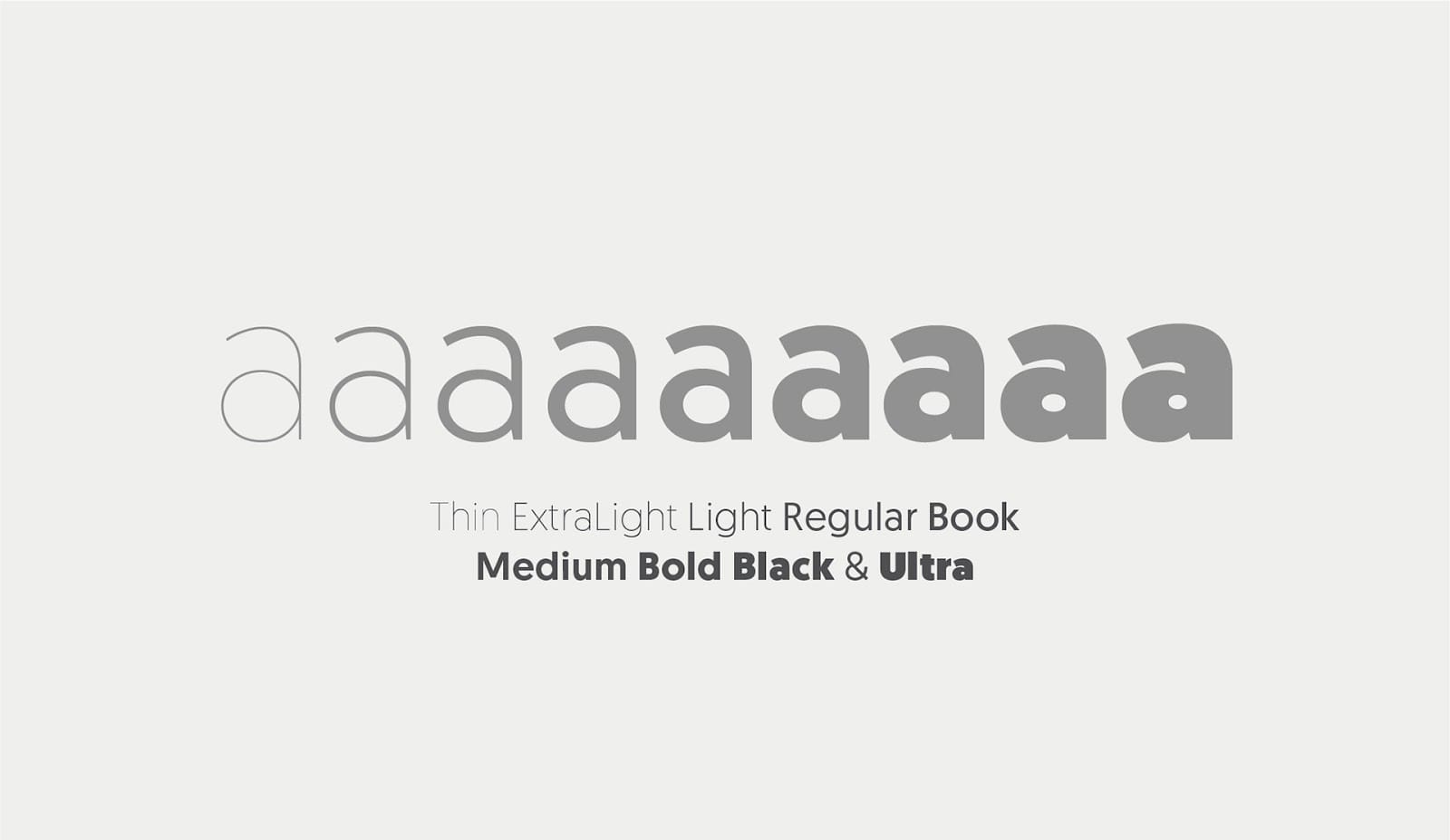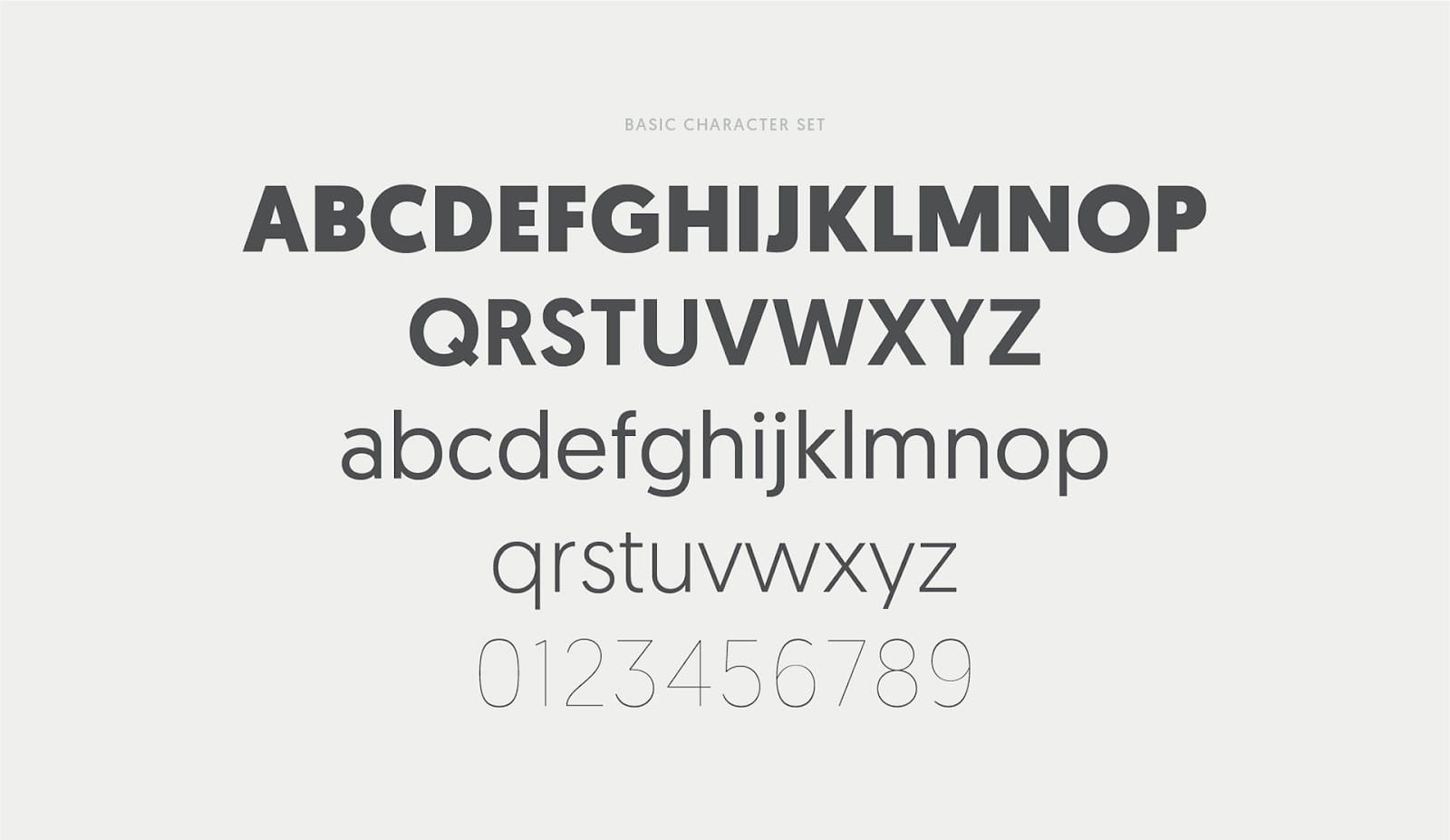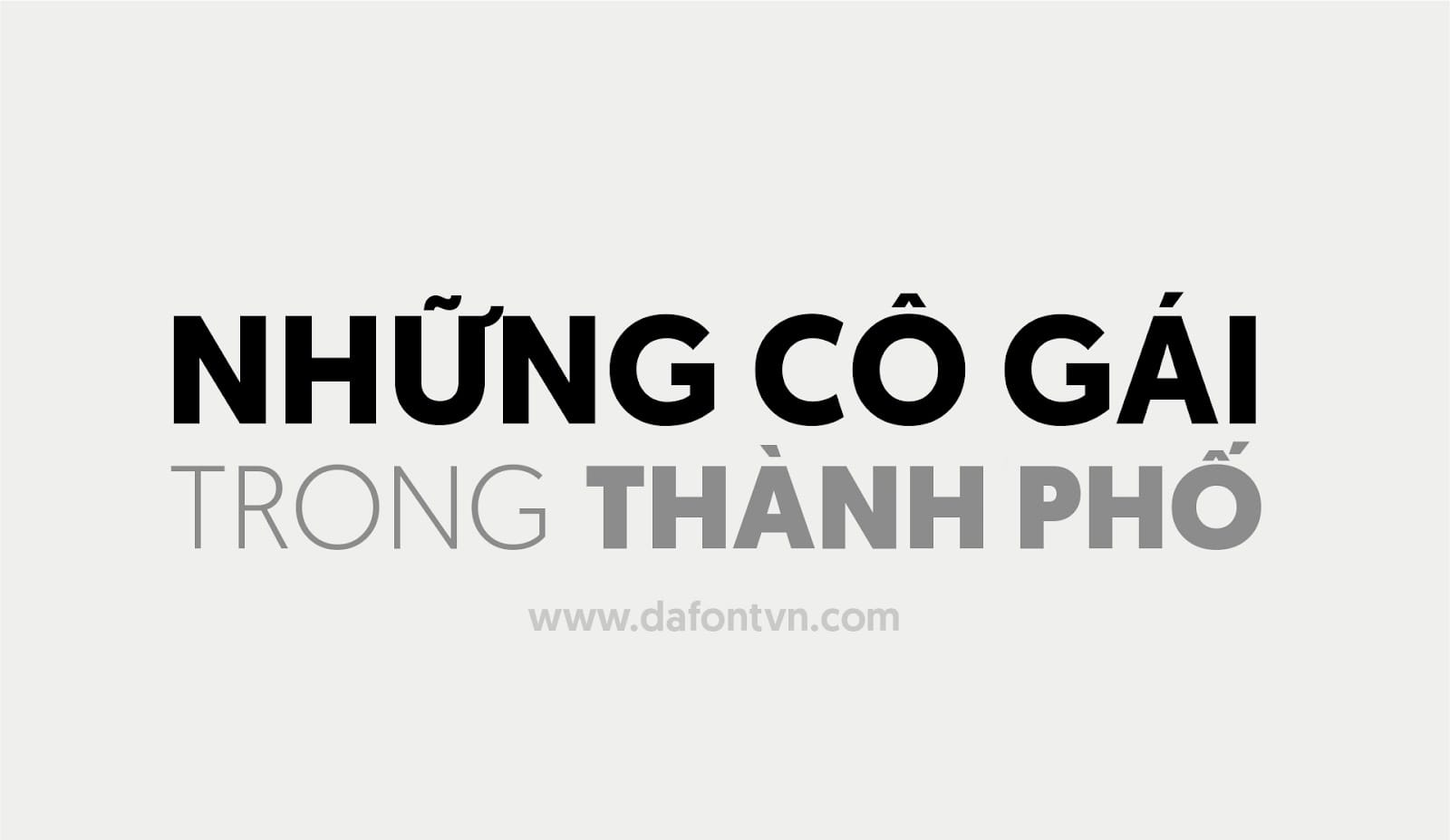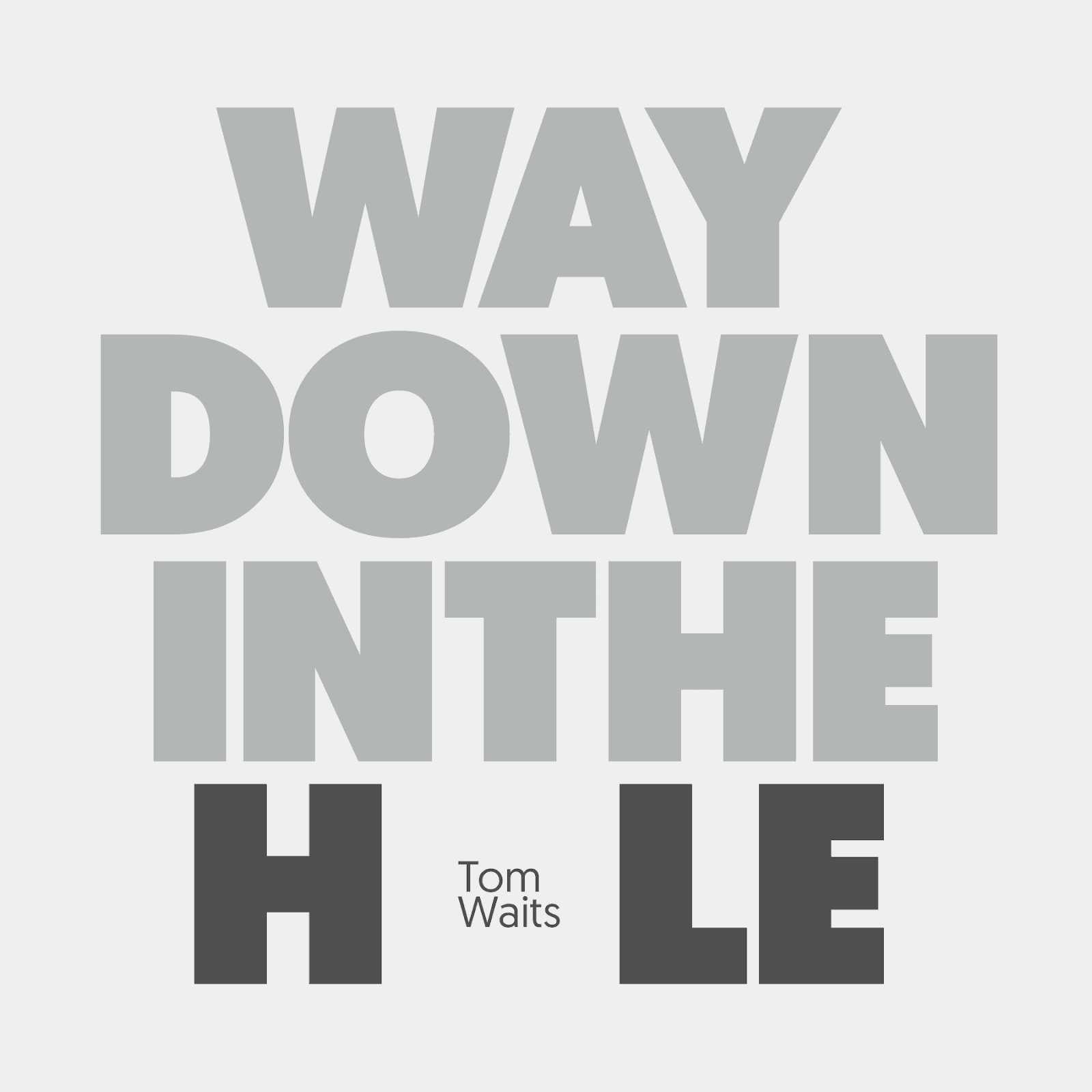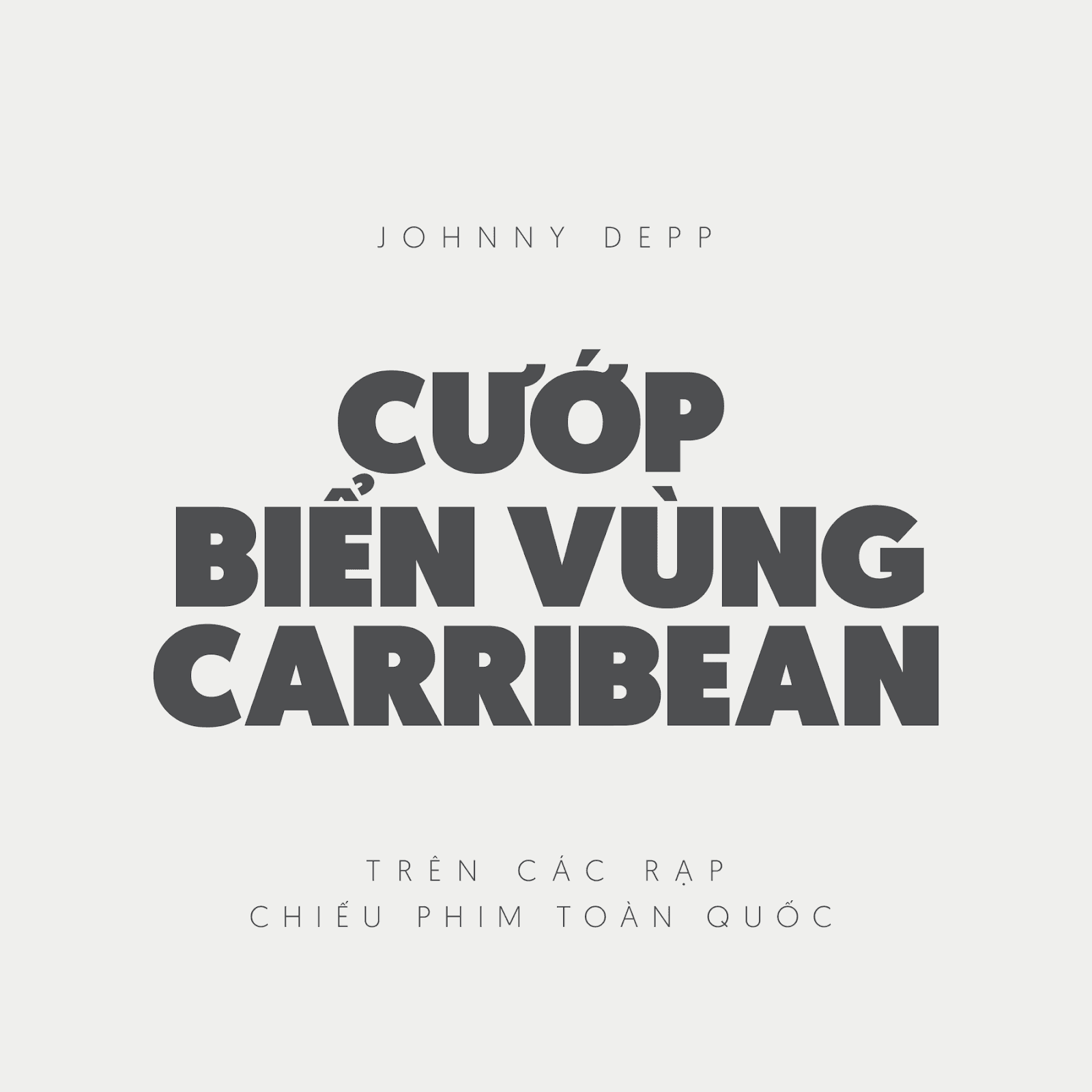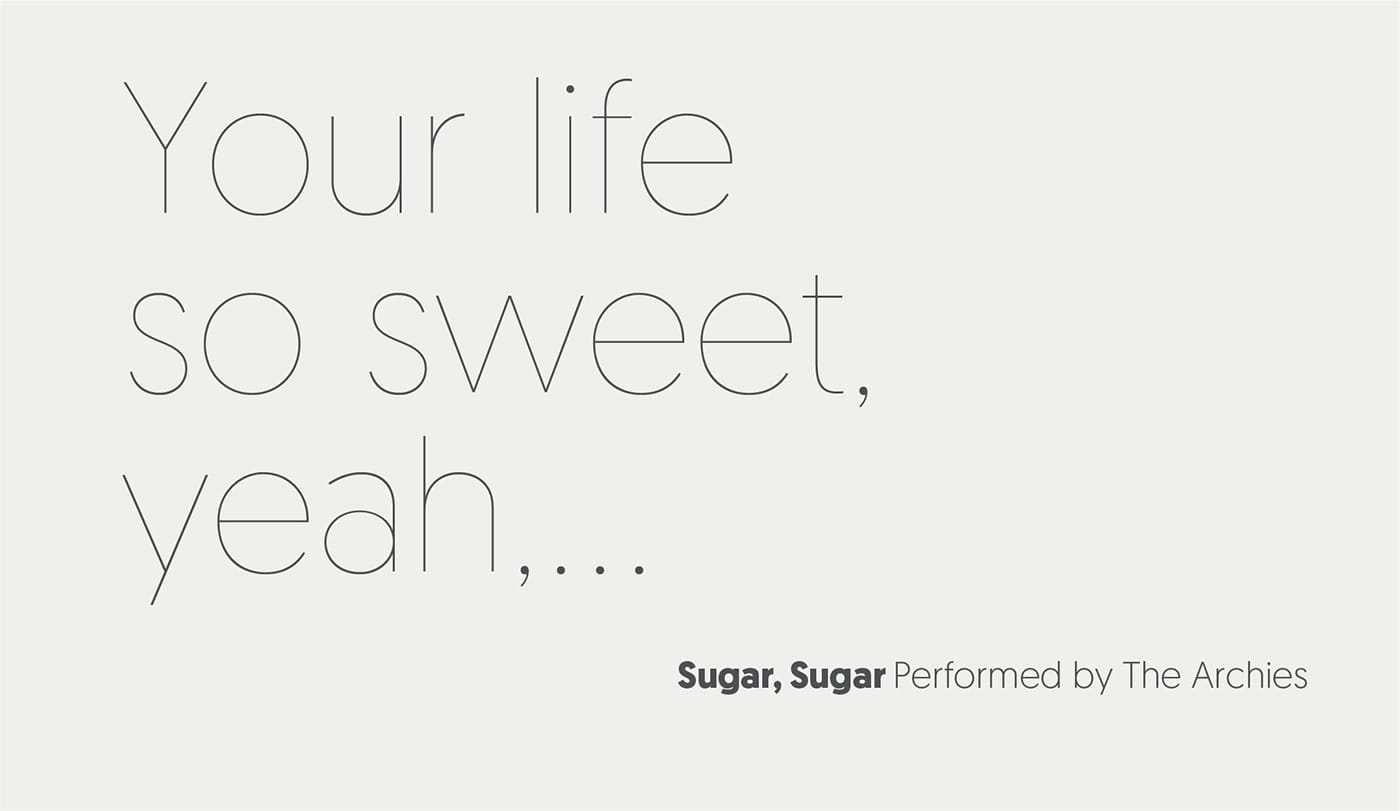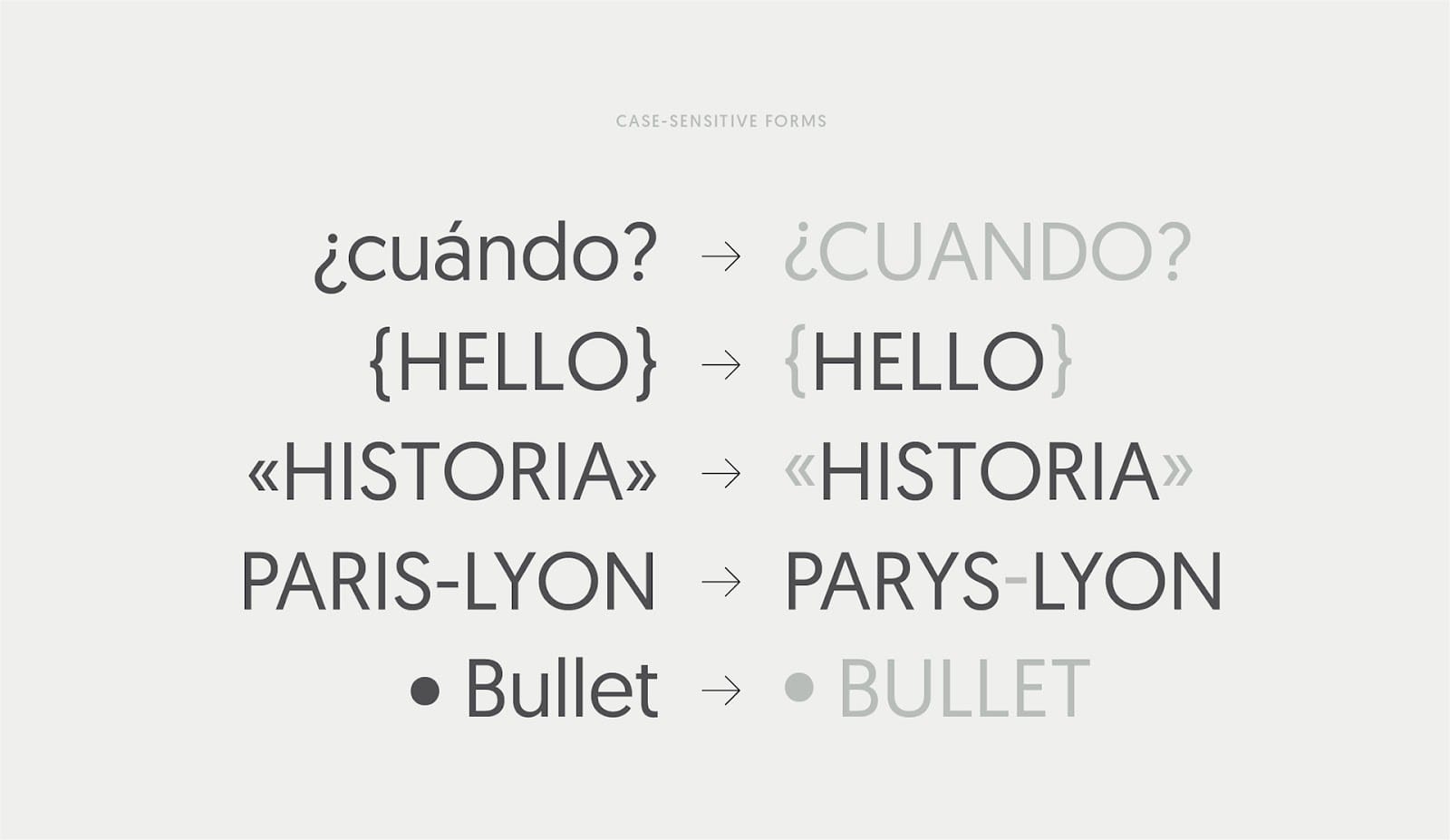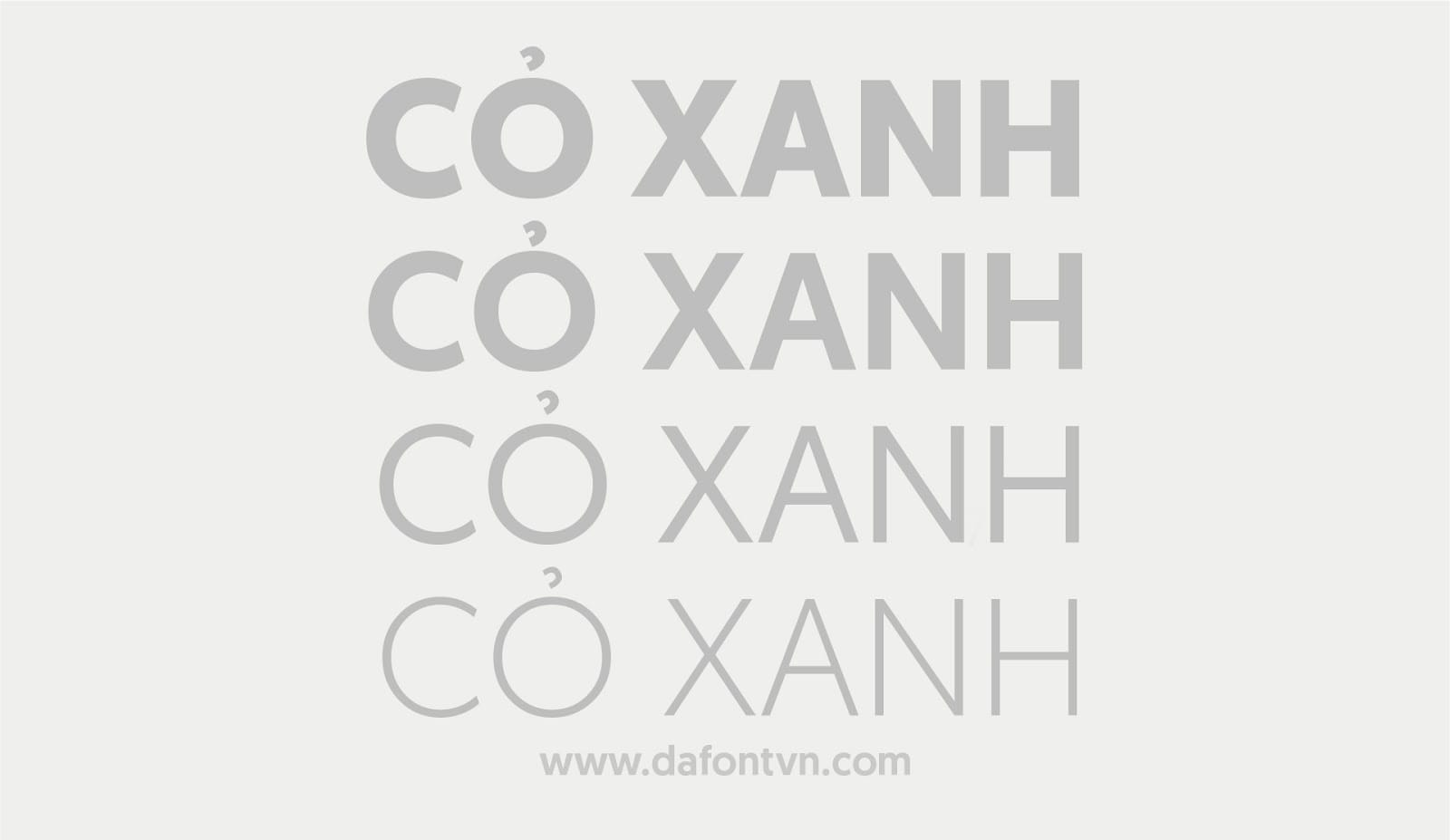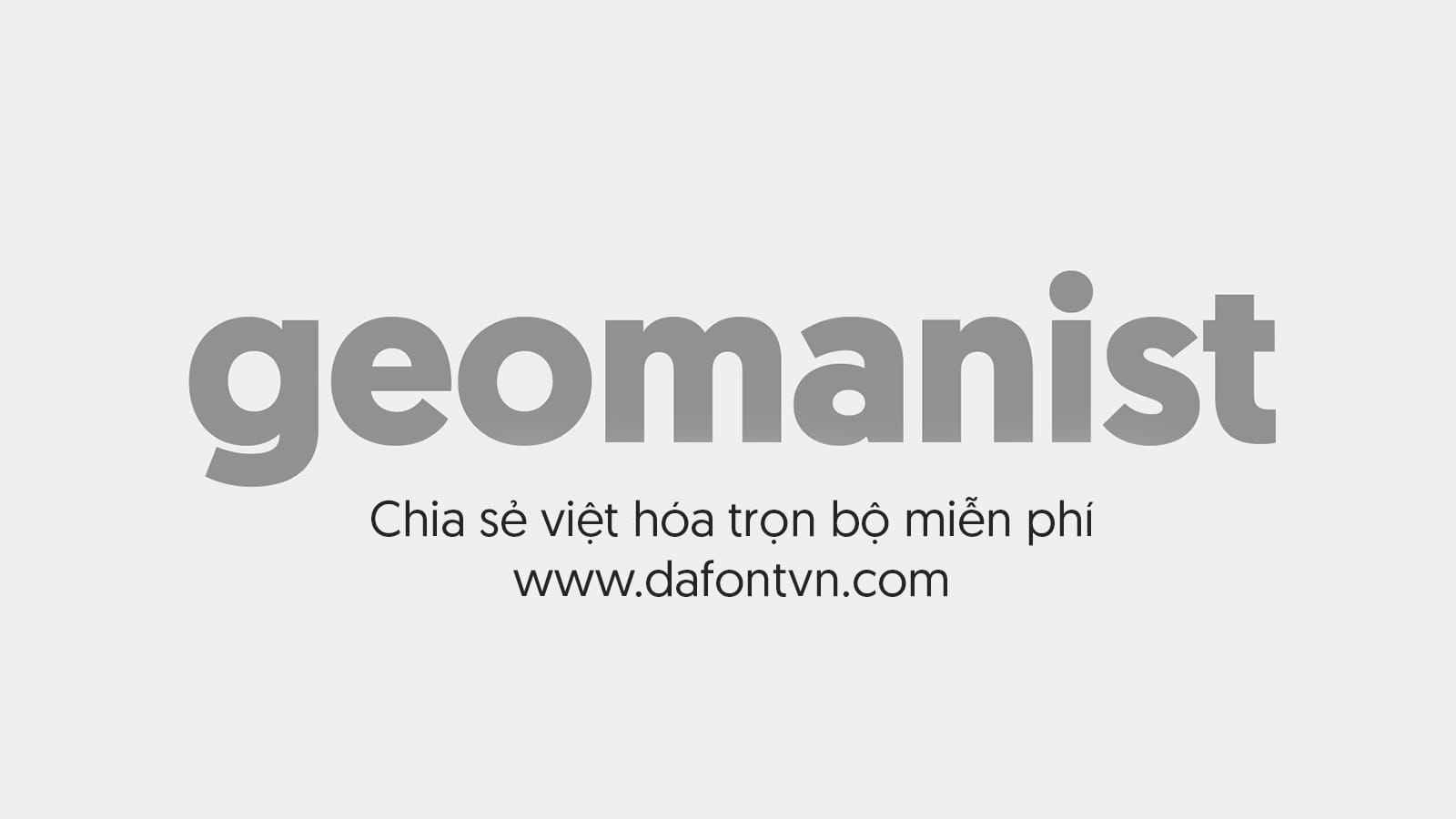
Font Geomanist Việt hóa trọn bộ (8 font)
Font Geomanist Việt hóa là một typeface hiện đại phù hợp với rất nhiều các thiết kế như xây dựng thương hiệu, thiệp cưới, thiệp mời, bao bì, blog, typography… vì là bộ font chữ với 8 kiểu khác nhau từ Thin mềm mại sang trọng cho đến Ultra siêu đậm vì vậy nó có thể sử dụng cho cả làm tiêu đề ngắn hoặc dài.
Bộ font bao gồm 8 kiểu đã được việt hóa đầy, kerning và chỉnh sửa lại cho phù hợp với các dấu.